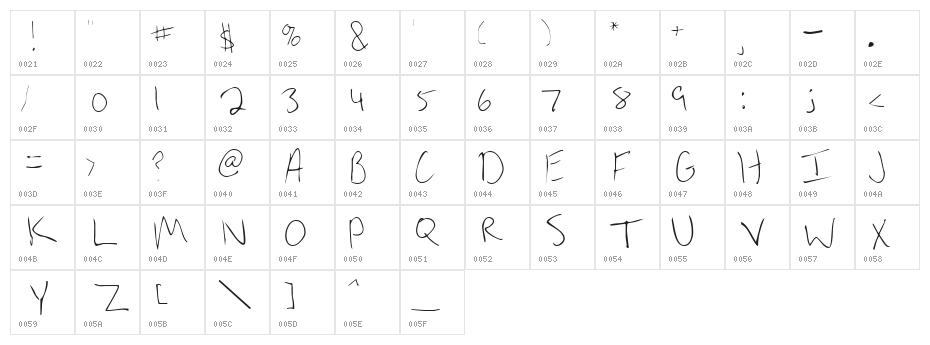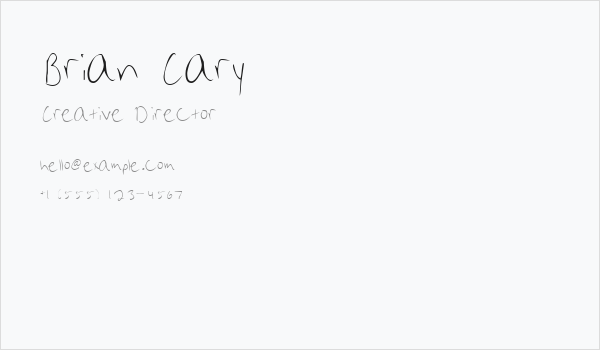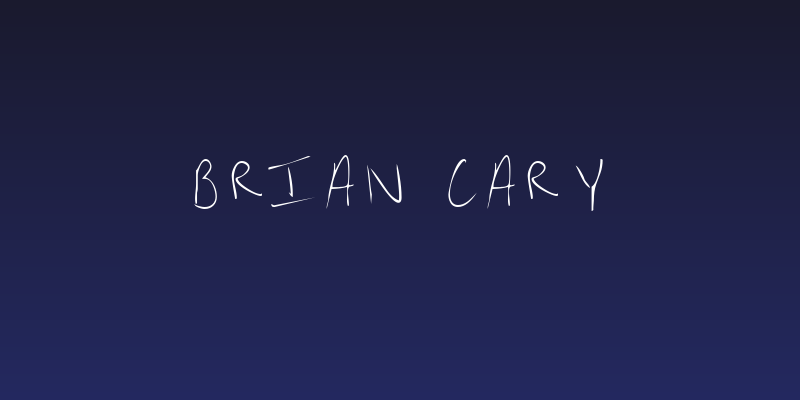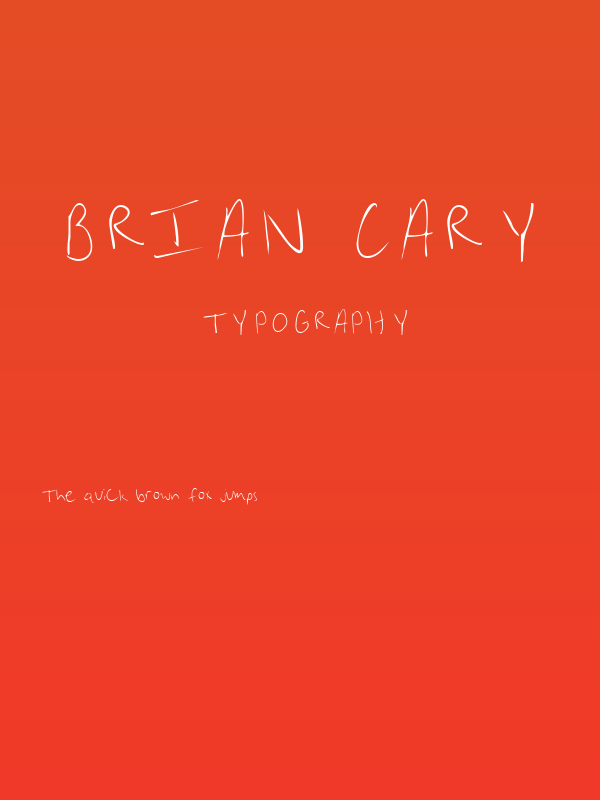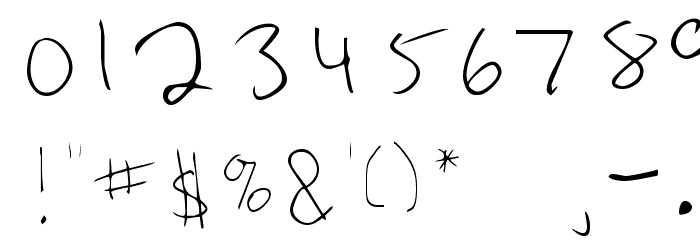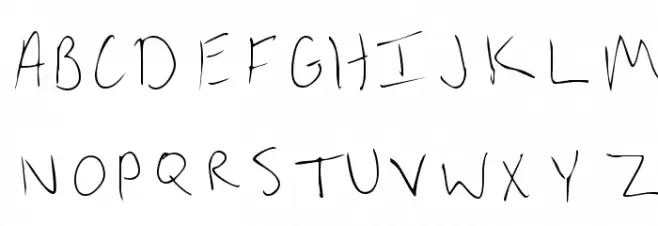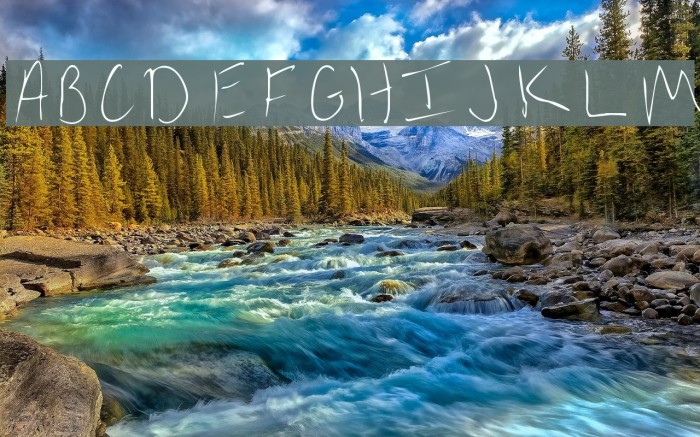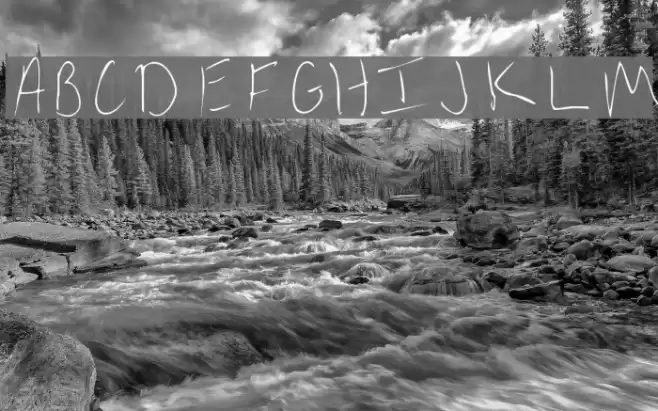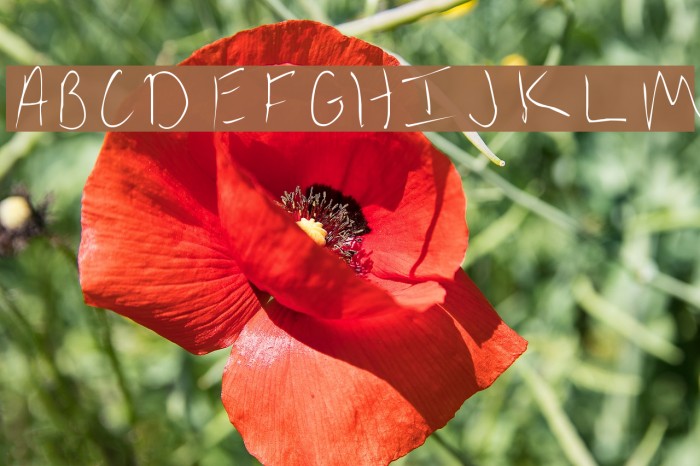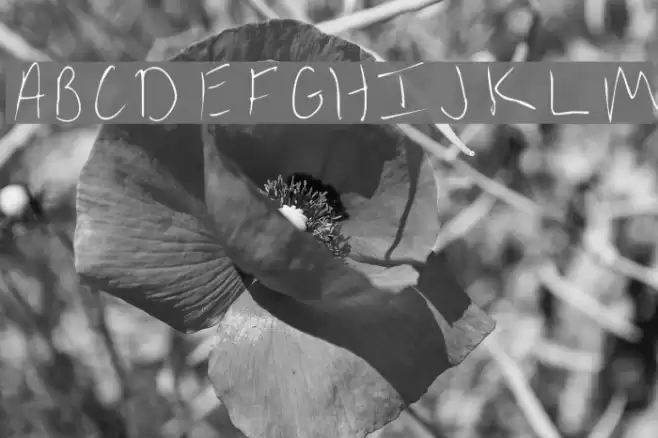
Brian Cary Font
✎ Quirky
| Categorias | Quirky |
| Estilo geral | Casual |
| Caso de uso | Logos, Headlines, Informal Text |
| Projetos propostos | Ideal for personal notes, greeting cards, informal invitations, and creative projects that require a touch of personality. |